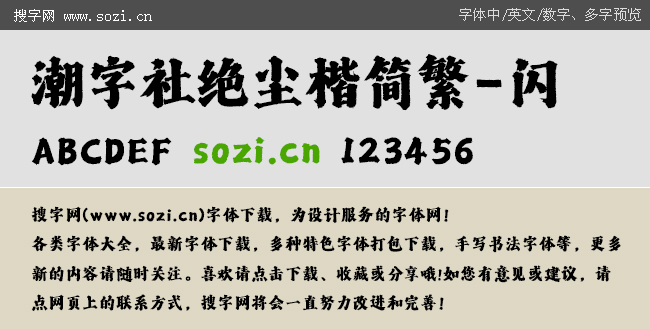
潮字社絕塵楷簡繁-閃
搜字網(wǎng)提供一款潮字社絕塵楷簡繁-閃中文字體下載,潮字社絕塵楷簡繁-閃是一款自然手寫楷體,字形古樸穩(wěn)重大氣,起收筆方圓結(jié)合,粗細(xì)對比強(qiáng)烈,從字形到筆畫,無不透露著沉穩(wěn)與灑脫。適合應(yīng)用于藝術(shù)設(shè)計(jì)、平面宣傳設(shè)計(jì)、網(wǎng)頁設(shè)計(jì)等領(lǐng)域等應(yīng)用。(本字體為個(gè)人非商用版,商用請聯(lián)系作者購買授權(quán)。官方網(wǎng)址:http://www.reeji.com 聯(lián)系方式:021-58597892)